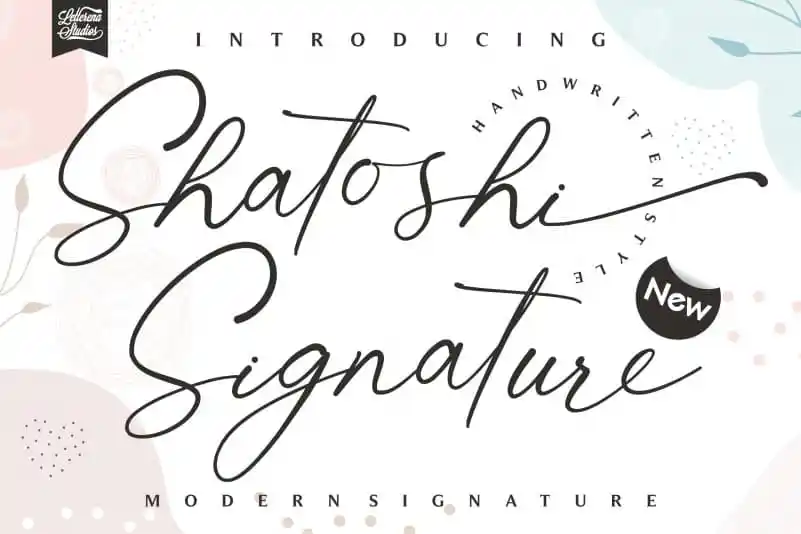
Shatoshi Signature Script Font – Download Grátis
A Shatoshi Signature Script Font é uma escolha perfeita para quem busca uma fonte escrita a mão com características elegantes e delicadas. Perfeita tanto para aplicações empresariais quanto para design gráfico, essa fonte manuscrita oferece um toque de refinamento que não passará despercebido em qualquer projeto. Com sua vibe limpa e suave, ela complementa perfeitamente qualquer marca, embalagem de produto, convite ou até mesmo a etiqueta de um lanche caseiro para o seu tênis recém-ascendido. Seja qual for o seu objetivo, seja ele criar uma identidade visual impactante, personalizar uma t-shirt ou criar um poster cheio de charme, Shatoshi Signature Script Font certamente será um elemento indispensável do seu design. Ideal tanto para criação de logotipos quanto para estender a sua presença na mídia social e em materiais promocionais.